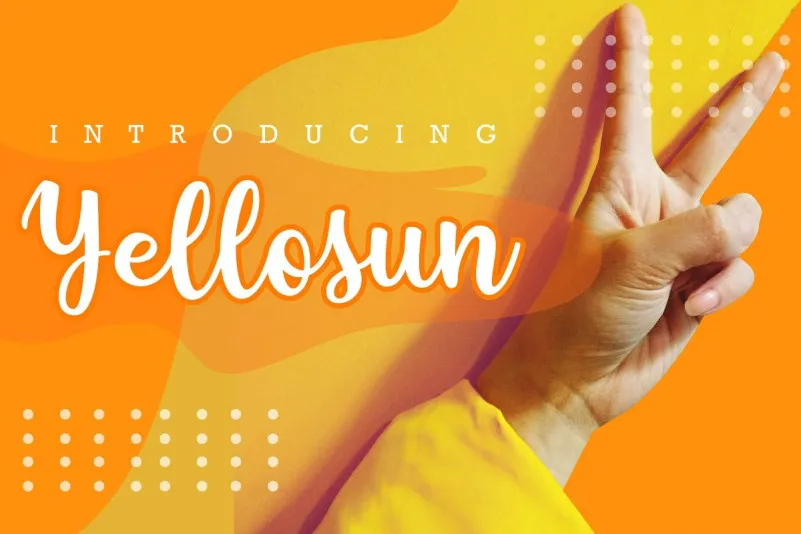
Yellosun Script Font – Download Grátis
Descobrimos uma nova fonte chamada Yellosun Script Font que certamente irá enriquecer seus projetos digitais com estilo e personalidade. Este é um script font único, criado pela GemesFont sob a autoria de zziplex. Com letras em tons de cores vivas e ilustrações vectoriais, este conjunto de fontes é perfeito para inscrições e design gráfico. O Yellosun Script Font tem um estilo singular que o torna ideal tanto para design editorial quanto para criação de logotipos ou identidade visual. Suas letras levemente decorativas combinam uma pitada descontraída com a elegância do texto, fazendo deste um recurso perfeito não apenas para nomes e mensagens, mas também para cartões de visita, selos, convites de casamento, materiais promocionais e até mesmo como parte da sua identidade visual. Com essa fonte à sua disposição, você pode criar designs que ressaltam suas habilidades criativas enquanto adiciona um toque de personalização aos seus projetos. Sempre lembrando de manter a qualidade do texto com o Yellosun Script Font.